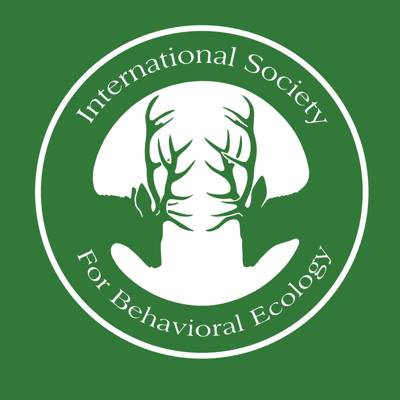
Society for Behavioral Ecology Logo: Schrift verzerrt?
ich brauche auch mal Hilfe bei der Identifikation einer Schrift. Hier ist das brandneue Logo der ISBE (Internation Society for Behavioral Ecology). Ich hatte eigentlich einen Entwurf für die gemacht, aber sie haben mein Design von jemand anderem komplett ummünzen lassen. Nur die Tierart ist geblieben. (Alles ganz legal, aber trotzdem ärgerlich.)
Nun hat das neue Logo eine mir unbekannte Schrift, ich habe jedoch den Eindruck, dass die relativ unprofessionell da reingequetscht wurde. Oder ist die wirklich so weit? Kann mir wer helfen. Einzelne Buchstaben sehen aus wie eine vertikal gequetschte Baskerville (passt aber nicht mit dem e, a und B).
Sonstige Kritik an dem Logo ist natürlich gern gesehen. ;-)
die von Dir genannten Symptome sind typisch für die ITC-Schriften. Da muss der Designer weniger verzerren um eine verzerrten Eindruck zu erhalten. Möglicherweise war die Tatwaffe eine ITC-Baskerville Light? Schade um die schöne Grafik ... mit passender Schrift hätte daraus ein gutes Logo werden können. Na ja ...
Stimmt, die Americana sieht dem ganz schön ähnlich. Dann hätte ich dem Designer da wohl unrecht getan. Leider habe ich keine bessere Auflösung des Logos gefunden, aber auf Anhieb sieht es so aus, als wäre das "e" und das "c" bei der Americana im Auslauf wesentlich schmaler.
Die Kleinbuchstaben g und t passen auch nicht. Aber nachdem die Schrift generell nicht zur Grafik passt, passt es ja irgendwie wieder?